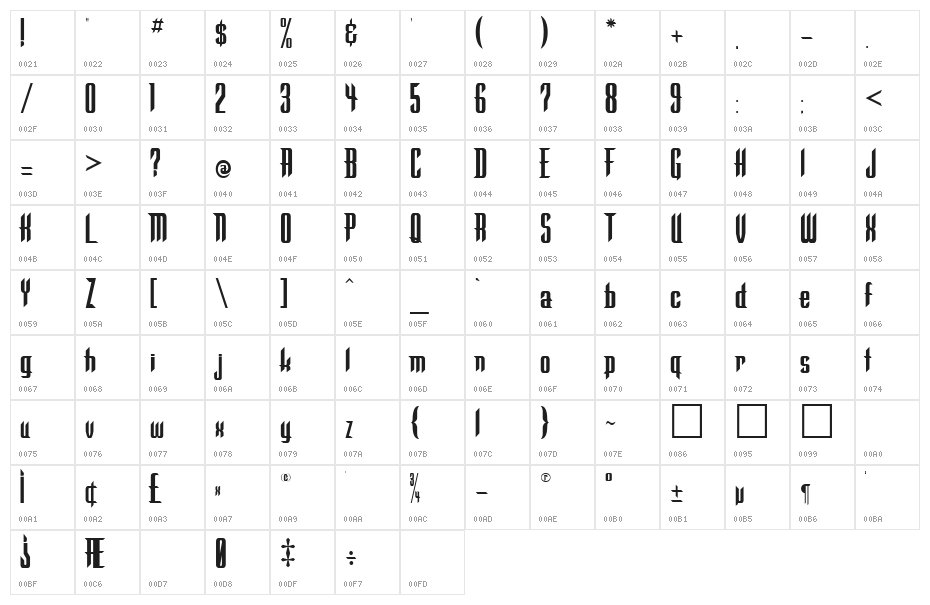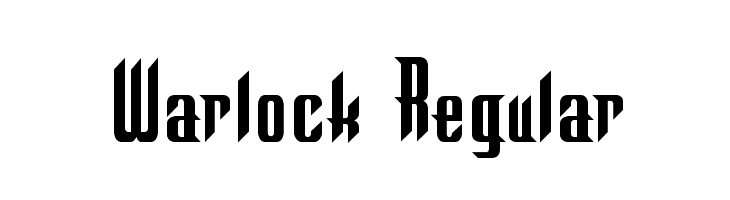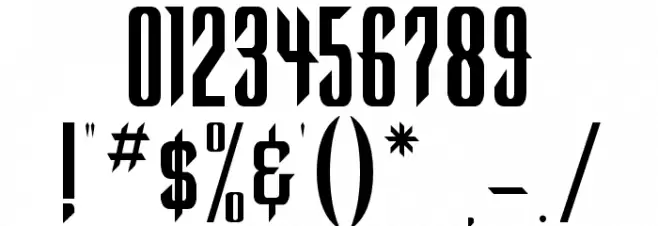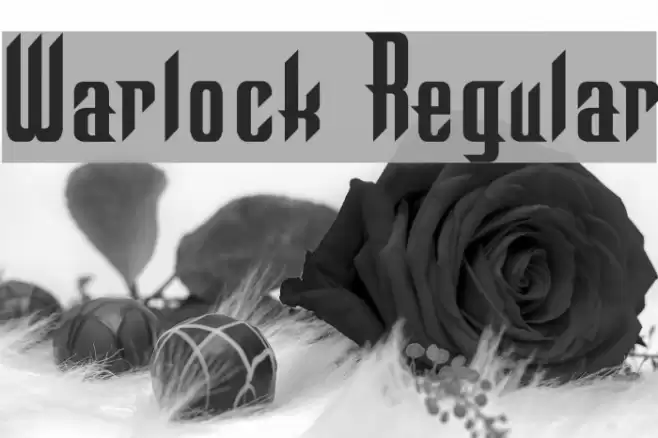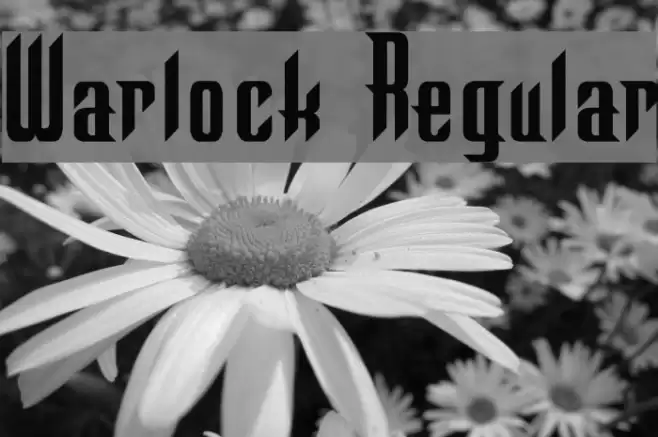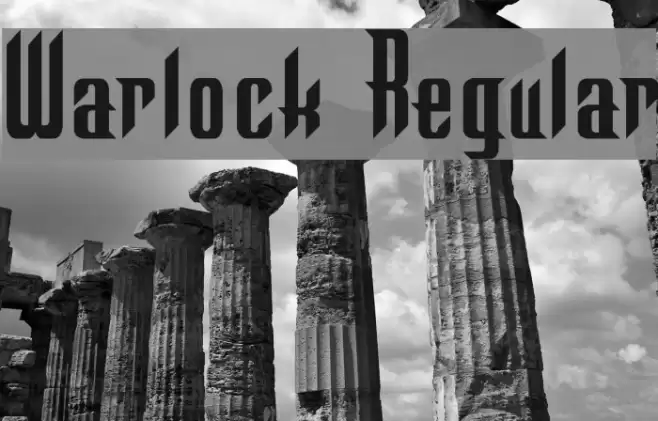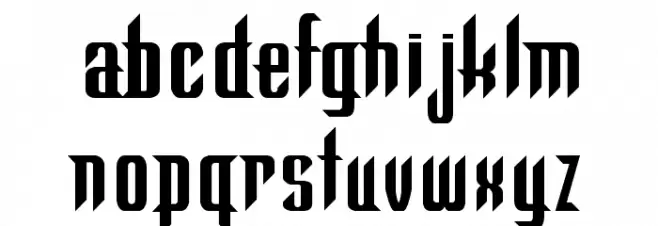
Warlock Regular Font
✎ Gothic
| おすすめプロジェクト | Ideal for use in posters, album covers, video game titles, and branding that requires a bold statement. |